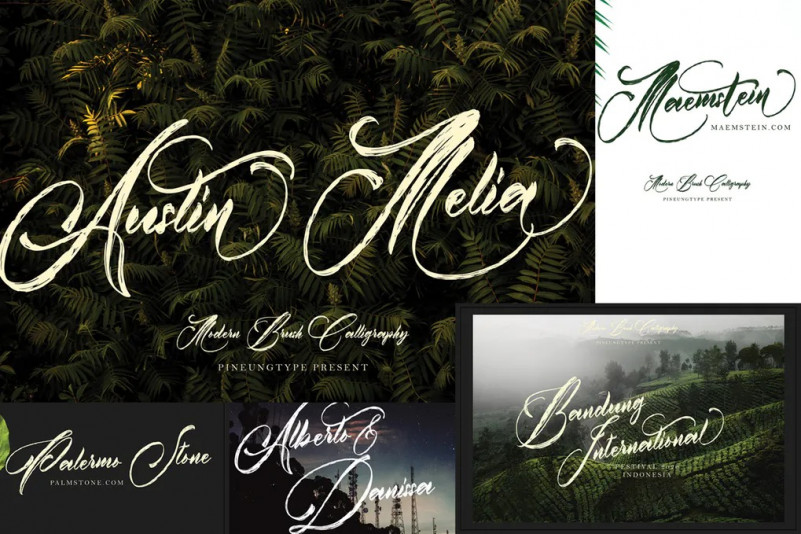
Austin Font
Austin pinceau police avec un nouveau style, cette police sera parfaite pour de nombreux projets différents ex : citations, Logo, en-tête de blog, affiche, baguage, mode, vêtements, lettre, invitation, papeterie, etc…